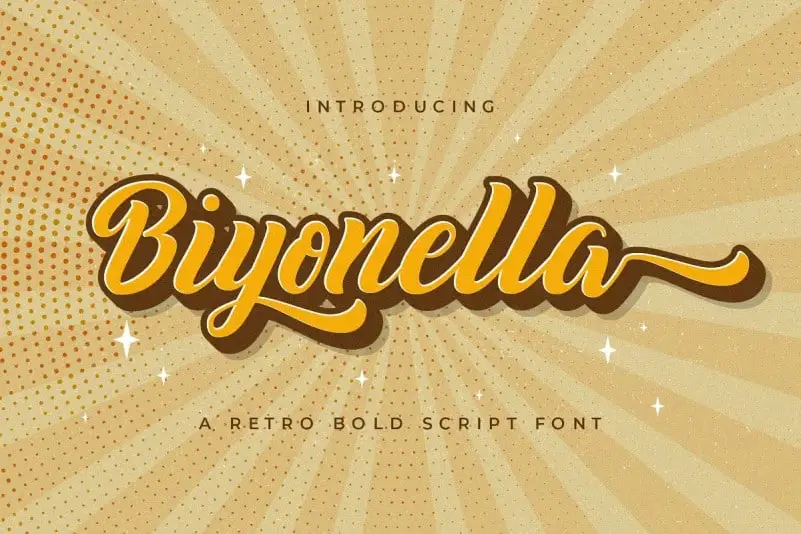
Biyonella Bold Script Font – Download Grátis
A Biyonella Bold Script Font é uma elegante tipografia feita à mão que oferece uma camada única de sofisticação. Com seu estilo vintage moderno e suas curvas arredondadas, ela está criada para deixar sua marca ainda mais respeitável. Perfeita tanto para criações bem pensadas quanto para adicionar um toque refinado a projetos, esta fonte irradia elegância em qualquer aplicação visual. Seja você um designer criativo ou estiloso que busca dar vida aos seus conceitos inovadores e originais, a Biyonella Bold Script Font tem tudo o que precisa para torná-los ainda mais impactantes.